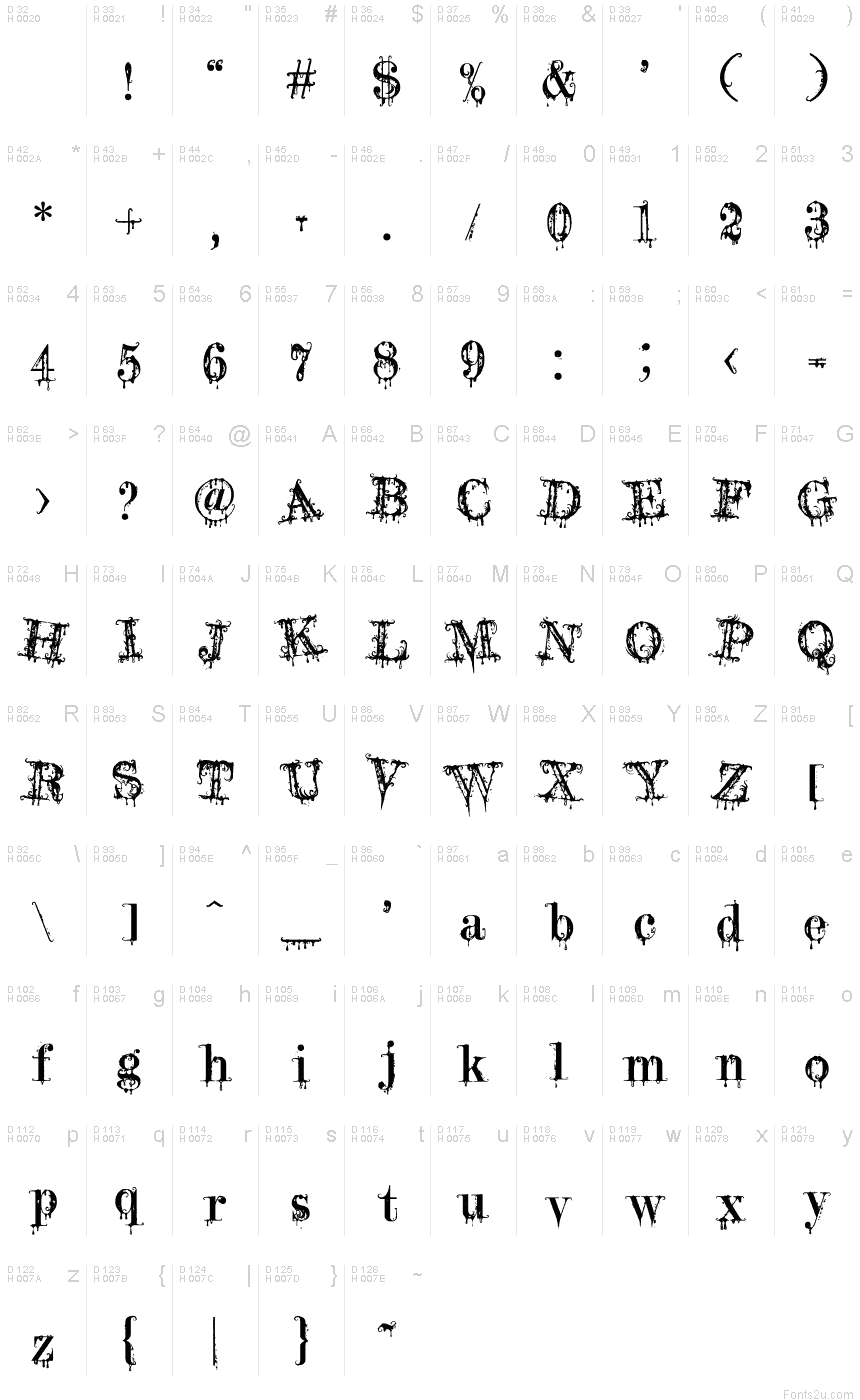
A Lolita Scorned
«A Lolita Scorned» — это завораживающий акцидентный шрифт, от которого веет леденящим готическим шармом. Созданный Йованой Гаспар АнжелиК (Jovana Gaspar AngeliQ), этот шрифт мастерски сочетает элегантные курсивные штрихи с грозными, рваными краями, создавая визуально впечатляющую и тревожную эстетику. Сложные, почти призрачные формы букв пробуждают ощущение тьмы и тайны, делая этот шрифт идеальным выбором для хоррор-дизайна, книжных обложек и других проектов, требующих смелого и зловещего визуального акцента.
Универсальный и приковывающий взгляд, «A Lolita Scorned» эффективно работает в самых разных дизайн-контекстах: от киноплакатов и обложек альбомов до оформления квестов в жанре хоррор и материалов к Хэллоуину. Его уникальный характер и призрачная привлекательность делают его отличным выбором для тех, кто хочет передать готическое беспокойство или создать макабрическую, сверхъестественную атмосферу.